KICKOFF
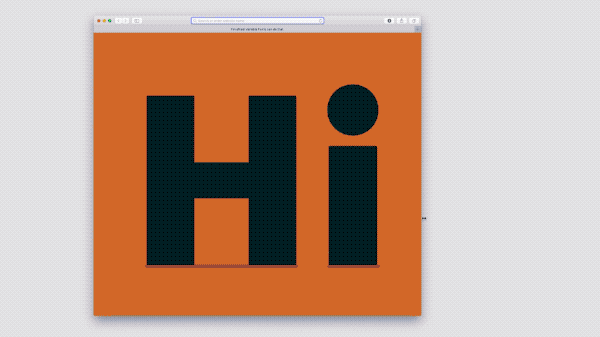
Vanaf het moment dat variable fonts werden geïntroduceerd (op 14 september 2016) ben ik gefascineerd door de techniek. Het geeft letterontwerpers veel creatieve vrijheid, zowel qua nieuwe expressievormen als qua typografische verfijning. Het voegt nieuwe dimensies aan typografie toe (motion, programmeerbaarheid) en blaast oude kwaliteiten nieuw leven in (optical size, grade).
Maar... hoe maak je eigenlijk een variable font? Dat vroegen Thomas Dahm en ik ons twee jaar geleden af. We gingen op zoek naar een maestro die het ons kon leren. Die vonden we in Arthur Reinders Folmer (aka Typearture). En om die kennis niet alleen voor onszelf te houden, organiseerden we vier workshops met meer dan 100 deelnemers.
Die workshops vormden de basis voor de Variable Font Course, waar we de afgelopen tijd aan hebben gewerkt. Arthur leert je in 11 videolessen hoe je een variable color font maakt, het verwerkt in HTML/CSS en laat animeren in de browser. Kijk maar:
Tha trailer
Ons doel is om variable fonts toegankelijk te maken voor een zo groot mogelijke groep ontwerpers, developers, type lovers, studenten en andere creatieven. De cursus is helemaal herschreven en up-to-date gemaakt. In een paar uurtjes heb jij je eerste variable font gemaakt, hoe vet is dat :)
Dit ga je leren:
Arthur Reinders Folmer is dus de cursusleider, een van de meest toonaangevende typografen in de variable font wereld. Hij won prijzen van Communication Arts en de Type Directors Club. Z'n experimentele werk bestaat uit een Frankensteinse combinatie van variable fonts, color fonts en illustratie. Letterontwerper Ulrike Rausch noemde hem niet voor niets "the absolute craziest variable color font designer on planet earth!”
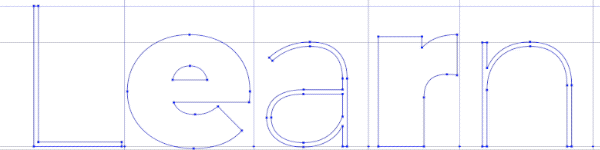
Ik ben super excited over de lessen die Arthur heeft samengesteld. Het is helemaal geworden wat ik had gehoopt: praktisch, inhoudelijk en leuk :) Heel tof dat we de cursus eindelijk openbaar kunnen maken; Arthur, Thomas en ik hebben er hard aan gewerkt. Ik ben benieuwd wat jij ervan vindt – laat het me weten!
Alles wordt stap voor stap uitgelegd, van een basic lettertype ontwerpen in Glyphs tot het interactief maken van het variable font in de browser
Voor elk niveau, van beginner tot ervaren type designer
Why Horizontal Lists Are Better for Mega Menus — uxmovement.medium.com
Mocht je een mega menu aan het ontwerpen zijn, overweeg dan om de items horizontaal ipv verticaal te ordenen.
AI in digital design: is menselijke creativiteit straks overbodig? — www.frankwatching.com
Voor Frank Watching schreef ik een column over de invloed van AI op digital design. Goed getimed met de release van DALL-E2......
IN JE FACE
"A potato wearing a trench coat in a heroic pose, 3d digital art"
DALL-E heeft een update gekregen en wat voor een. Het AI-systeem dat omschrijvingen in mensentaal omzet in gegenereerde visuals is nu nog sneller, specifieker en in hogere resolutie. Echt mind blowing 🤯 Lees en zie er alles over:
Demos by Karen X. Cheng (Twitter)
Meet DALL-E, the A.I. That Draws Anything at Your Command (The New York Times)
Playing with DALL·E 2 (LessWrong)
Kushagra Gupta's 3D-designs zijn een mystieke mengelmoes van cyber punk, Y2K, bio art en gothic. Heel gaaf.
MUST: DIDIER CATZ
Didier is Halfvetter, interdisciplinair ontwerper en creatief ontwikkelaar
App die ik net heb geïnstalleerd:
Quick Capture is een super minimalistische note-taking app voor iOS met audio en video ingebouwd. Je kunt notities maken doormiddel van je toetsenbord, microfoon of camera.